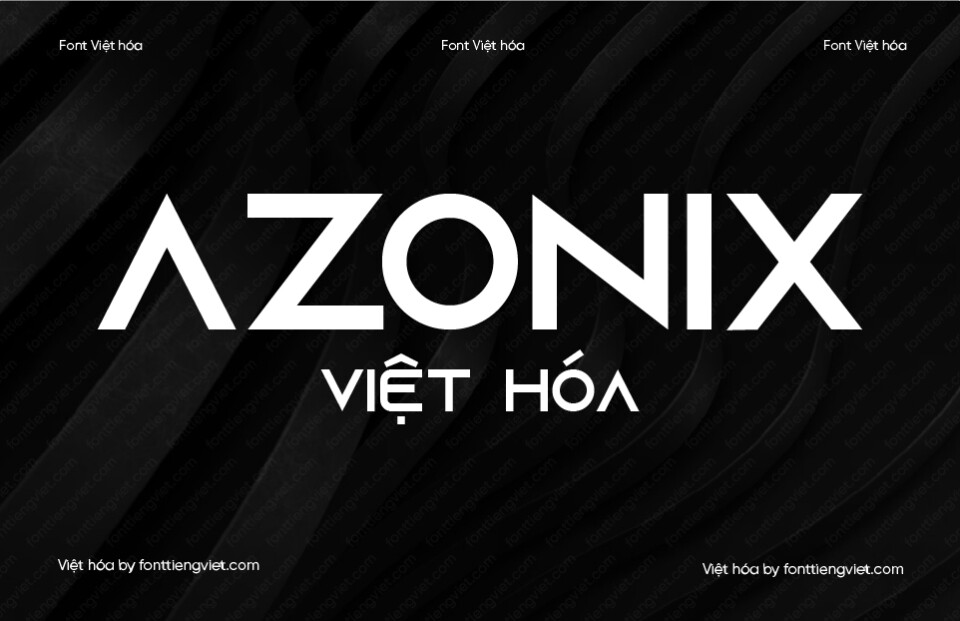
Font Việt hóa 1FTV VIP Azonix
Giới thiệu về Font Việt hóa 1FTV VIP Azonix trong thiết kế đồ họa
Trong kỷ nguyên số hiện nay, việc lựa chọn một bộ phông chữ phù hợp đóng vai trò quyết định đến sự thành công của một bản thiết kế. Font Việt hóa 1FTV VIP Azonix nổi lên như một lựa chọn hàng đầu cho những ai yêu thích phong cách tối giản, hiện đại và mang hơi hướng tương lai. Đây là bản tùy chỉnh đặc biệt từ bộ phông Azonix gốc, một kiểu chữ không chân (sans-serif) với các đường nét hình học sắc sảo, khỏe khoắn. Việc sử dụng Font Miễn Phí chất lượng cao giúp các bạn học sinh, sinh viên và những người mới bắt đầu làm quen với thiết kế có thêm công cụ mạnh mẽ để sáng tạo. Phiên bản này đã được xử lý kỹ lưỡng để hỗ trợ đầy đủ bộ gõ tiếng Việt, loại bỏ hoàn toàn nỗi lo lỗi font khi gõ các dấu thanh phức tạp. Nhờ đó, người dùng có thể thoải mái áp dụng vào các dự án từ học tập đến công việc chuyên môn mà không gặp bất kỳ rào cản kỹ thuật nào.
Những đặc điểm nổi bật của Font Việt hóa 1FTV VIP Azonix
Thiết kế hiện đại và đậm chất công nghệ
Đặc trưng lớn nhất của Font Việt hóa 1FTV VIP Azonix chính là sự kết hợp giữa các đường thẳng dứt khoát và các góc bo tròn tinh tế. Cấu trúc của từng chữ cái được tính toán theo tỷ lệ vàng, tạo ra sự cân đối thị giác tuyệt vời. Kiểu chữ này gợi liên tưởng đến các giao diện công nghệ cao, phim khoa học viễn tưởng hoặc các thương hiệu khởi nghiệp sáng tạo. Với độ dày nét đồng nhất, bộ font này duy trì được sự rõ ràng ngay cả khi hiển thị trên màn hình điện thoại nhỏ hay trên các tấm áp phích khổ lớn. Sự tối giản giúp người xem tập trung tối đa vào thông điệp mà người thiết kế muốn truyền tải.
Khả năng ứng dụng đa dạng trong thực tế
Mặc dù mang phong cách hiện đại, nhưng Font Việt hóa 1FTV VIP Azonix lại vô cùng linh hoạt. Bạn có thể sử dụng nó để làm tiêu đề bài thuyết trình PowerPoint, thiết kế bìa sách giáo khoa cách tân, hoặc làm logo cho các câu lạc bộ trong nhà trường. Trong lĩnh vực marketing, font chữ này cực kỳ hiệu quả khi dùng làm tiêu đề (headline) cho các bài đăng mạng xã hội như Facebook hay Instagram. Nó giúp thu hút ánh nhìn ngay lập tức nhờ vẻ ngoài chuyên nghiệp và sang trọng. Đối với các bạn học sinh đang thực hiện dự án truyền thông học đường, đây chính là “vũ khí” bí mật để tạo nên dấu ấn riêng biệt cho sản phẩm của mình.
Lưu ý khi phối màu và bố cục
Vì Font Việt hóa 1FTV VIP Azonix có cá tính rất mạnh, bạn nên ưu tiên sử dụng các bảng màu tương phản như trắng – đen, xanh neon – đen hoặc cam – xám đậm. Tránh việc nhồi nhét quá nhiều hiệu ứng đổ bóng hay viền chữ phức tạp vì bản thân cấu trúc chữ đã đủ ấn tượng. Hãy để không gian trắng xung quanh chữ được rộng rãi, giúp thiết kế của bạn trông “thở” hơn và mang lại cảm giác cao cấp, tinh tế. Đây là quy tắc vàng mà các chuyên gia thường áp dụng để tối ưu hóa hiệu quả thị giác của bộ font đặc biệt này.
Kết luận về bộ Font Việt hóa 1FTV VIP Azonix
Tổng kết lại, đây là một bộ công cụ không thể thiếu trong kho tài nguyên của bất kỳ ai yêu cái đẹp và sự hiện đại. Với khả năng hỗ trợ tiếng Việt hoàn hảo cùng phong cách thiết kế thời thượng, nó sẽ nâng tầm mọi dự án sáng tạo của bạn từ những chi tiết nhỏ nhất. Đừng ngần ngại trải nghiệm ngay Font Miễn Phí, Font Việt Hóa, Font Việt hóa 1FTV VIP Azonix để cảm nhận sự khác biệt và chuyên nghiệp mà nó mang lại. Chúc bạn có những sản phẩm thiết kế thật ấn tượng và thành công trên con đường chinh phục nghệ thuật chữ viết.